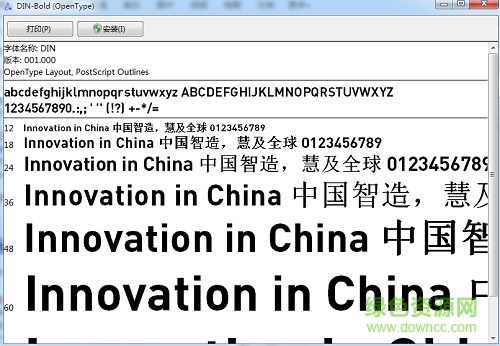
din bold粗體字體是一款專為需要用到各種藝術(shù)字體的朋友準備的英文字體,筆劃流暢,字型優(yōu)美,非常適合用來做各種標題的字體,有需要的朋友歡迎來綠色資源網(wǎng)下載使用!
din bold字體是一款專為用于藝術(shù)設計方面的字體用于藝術(shù)品裝飾設計,造型設計等字體史依弘的一種設計字體軟件,筆劃流暢,字型優(yōu)美,印刷效果好,適于報刊、雜志的正文。